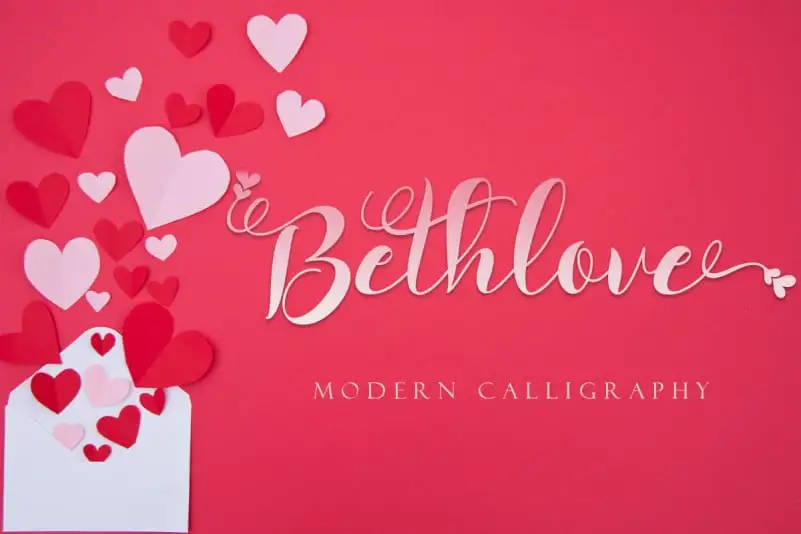
Bethlove Calligraphy Font
Bethlove Calligraphy Font é uma fonte moderna que apresenta letras únicas. Este tipo especializa-se em adicionar um toque de romance a qualquer projeto através de seu detalhe particular, conhecido como “swash”, formado pela forma corações. É perfeito para ocasiões românticas como o Dia dos Namorados e casamentos, bem como textos dedicatórios, promocionais para datas especiais ou atualizações nas redes sociais. Suas linhas elegantes e seus detalhes delicados criam um ambiente de autêntica sofisticação, tornando-a uma escolha perfeita para quem busca uma fonte chamativa que também possa ser discreta quando necessário. A Yoga Letter é a responsável por esse design único que enriquece qualquer projeto com seu charme inconfundível.